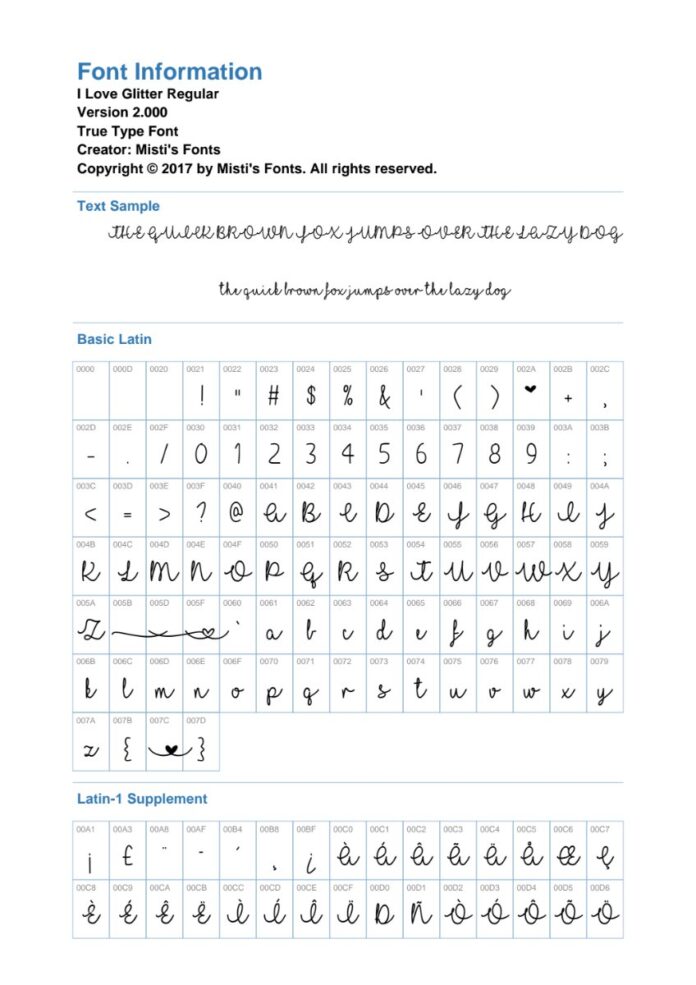
Trong thế giới thiết kế đồ họa, việc lựa chọn font chữ phù hợp có vai trò cực kỳ quan trọng, quyết định đến cảm xúc và thông điệp mà bạn muốn truyền tải. Font I Love Glitter – TTF là một trong những lựa chọn hàng đầu dành cho những ai yêu thích sự mềm mại, bay bổng và một chút lấp lánh, cá tính. Với thiết kế độc đáo, font chữ này đã nhanh chóng trở thành nguồn cảm hứng cho nhiều nhà thiết kế, đặc biệt trong các dự án cần sự tinh tế và nữ tính.
Đặc Điểm Nổi Bật Của Font I Love Glitter – TTF
Thiết Kế Độc Đáo và Tinh Tế
Font I Love Glitter nổi bật với các nét chữ viết tay mềm mại, uyển chuyển, mang đến cảm giác thân thiện và gần gũi. Mỗi ký tự được thiết kế tỉ mỉ, tạo nên sự hài hòa tổng thể, phù hợp với nhiều loại hình thiết kế khác nhau. Đặc biệt, font chữ này thường được kết hợp với hiệu ứng lấp lánh (glitter) để tăng thêm vẻ đẹp lung linh, quyến rũ.
Đa Dạng Ứng Dụng
Với phong cách độc đáo, Font I Love Glitter – TTF có thể được ứng dụng rộng rãi trong nhiều lĩnh vực:
- Thiết kế thiệp mời: Tạo điểm nhấn cho thiệp cưới, thiệp sinh nhật, thiệp chúc mừng với vẻ đẹp lãng mạn và cá tính.
- Thiết kế logo và branding: Phù hợp cho các thương hiệu thời trang, mỹ phẩm, trang sức, hoặc các doanh nghiệp muốn thể hiện sự sang trọng, nữ tính.
- Thiết kế bao bì sản phẩm: Giúp sản phẩm trở nên nổi bật và thu hút hơn trên kệ hàng.
- Thiết kế ấn phẩm truyền thông: Poster, banner, bài đăng mạng xã hội sẽ trở nên sinh động và cuốn hút hơn.
- Thiết kế sách, tạp chí: Tạo tiêu đề hoặc các đoạn văn bản đặc biệt, mang lại cảm giác nhẹ nhàng và dễ đọc.
Font I Love Glitter – TTF phù hợp với những loại thiết kế nào?
Font I Love Glitter – TTF rất phù hợp cho các thiết kế cần sự mềm mại, tinh tế và cá tính như thiệp mời (cưới, sinh nhật), logo, branding cho các thương hiệu thời trang, mỹ phẩm, trang sức, bao bì sản phẩm, poster, banner và các ấn phẩm truyền thông khác.